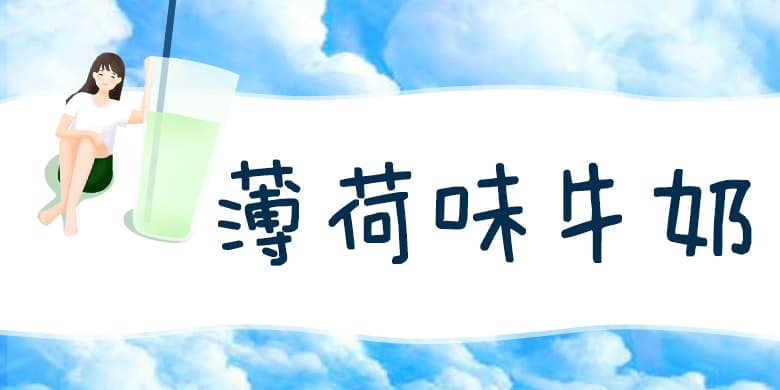
品牌:方正手迹设计师:刘晔发行时间:2018字库编码:大陆简体(GB2312-80)分类:创意书写字体属性:精品字
薄荷味牛奶这款字部件线条简洁,笔画排列打破常规横平竖直,字体整体向左倾斜给人感觉略带稚气又非常可爱,很有趣味性。适用于少年儿童类的书刊、品牌广告和产品包装设计,以及社交网络的个性化用字。